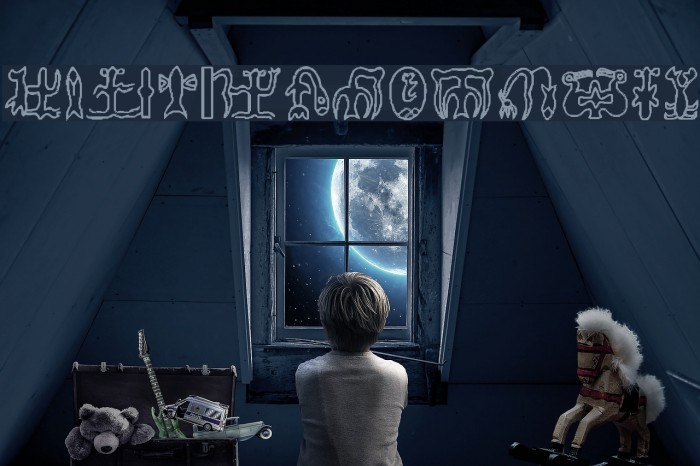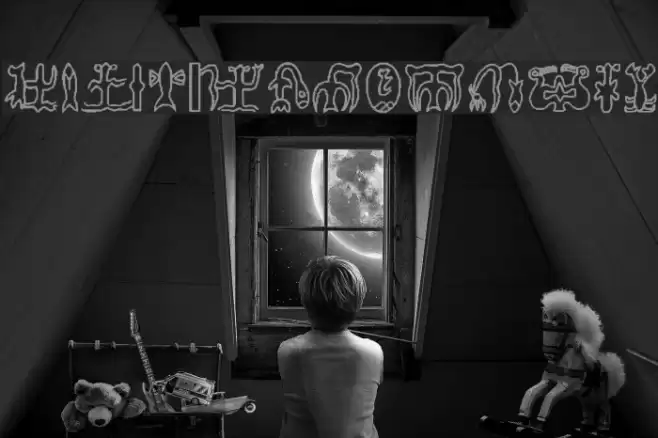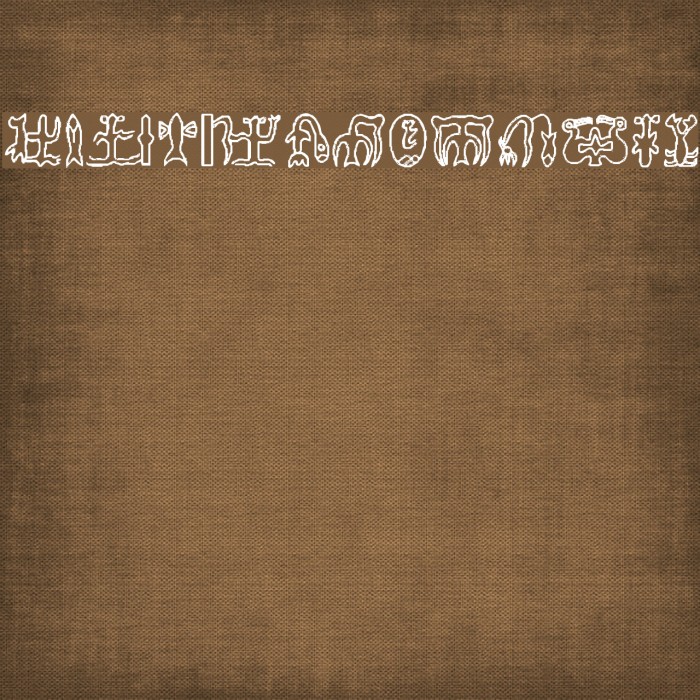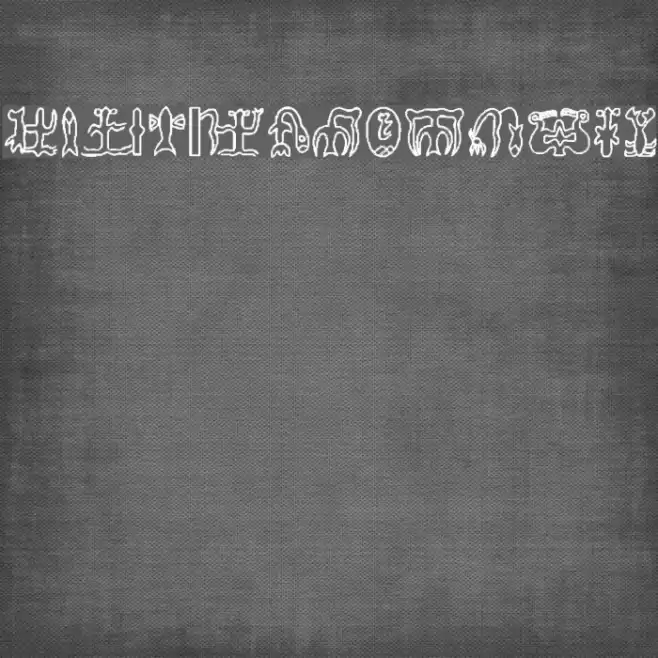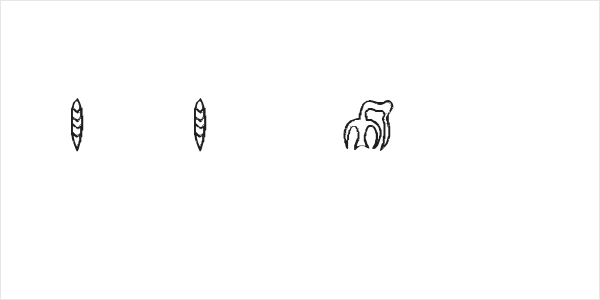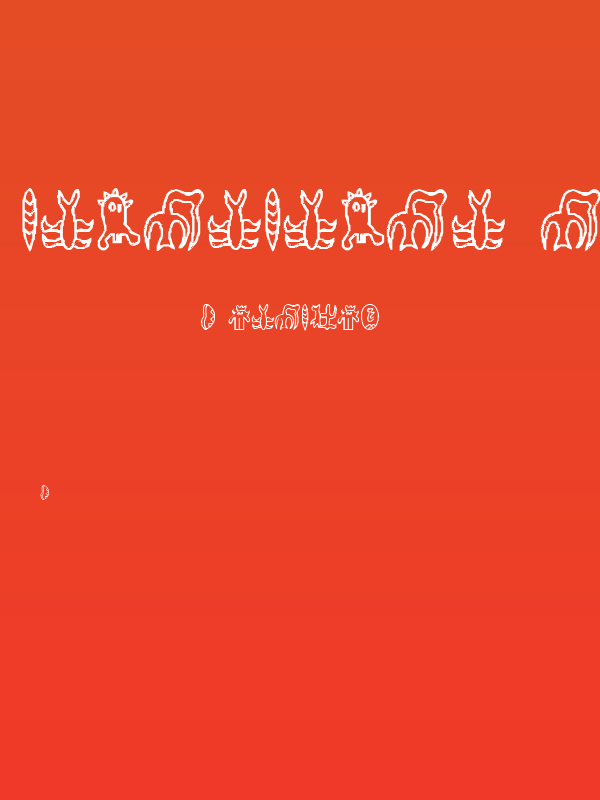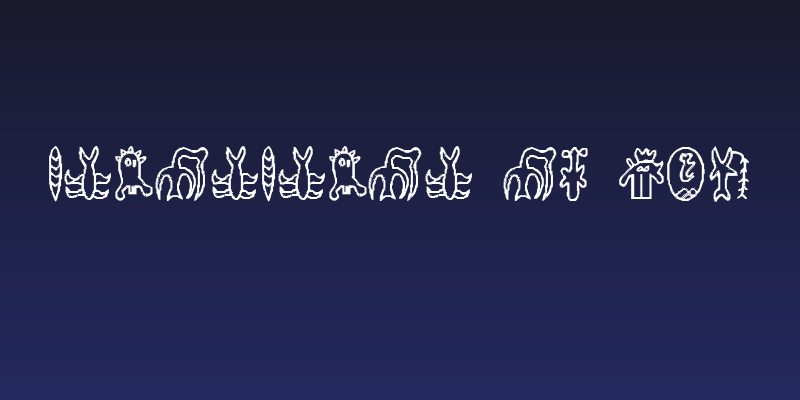
RongoRongo Glyphs Font
| Cas d'utilisation | Logos, Artistic designs, Thematic displays |
| Projets proposés | Ideal for projects that require a historical or cultural theme, such as museum exhibits, educational materials, or artistic designs that aim to evoke a sense of ancient mystery and storytelling. |